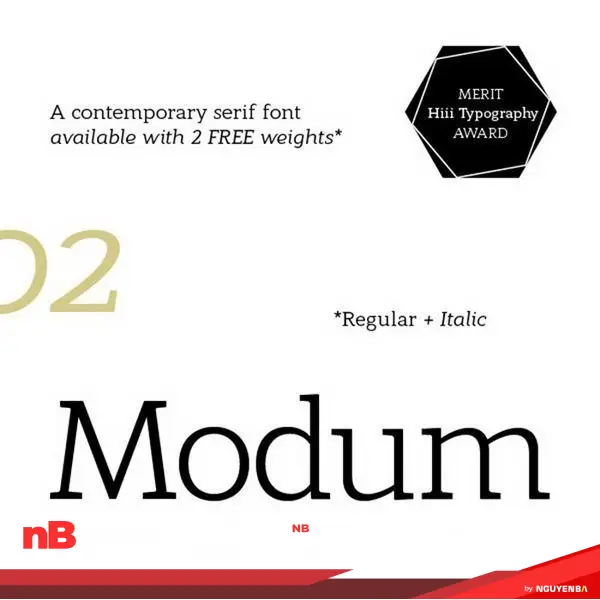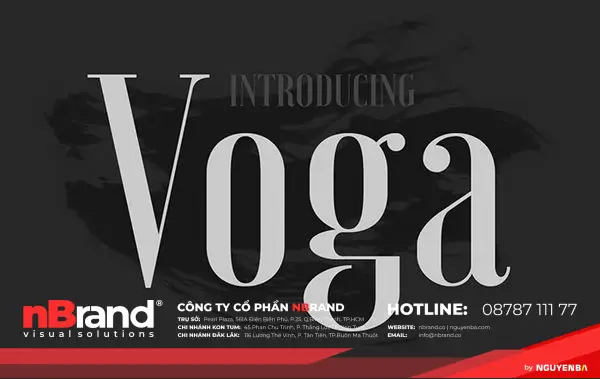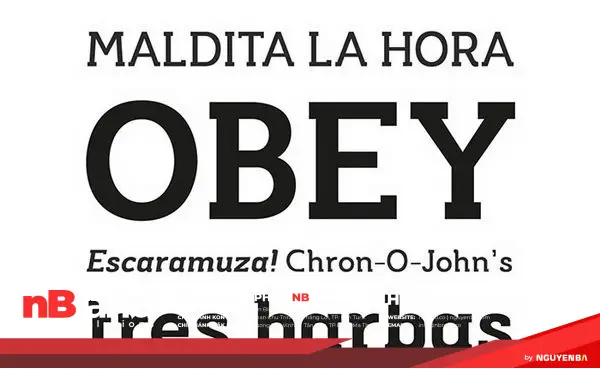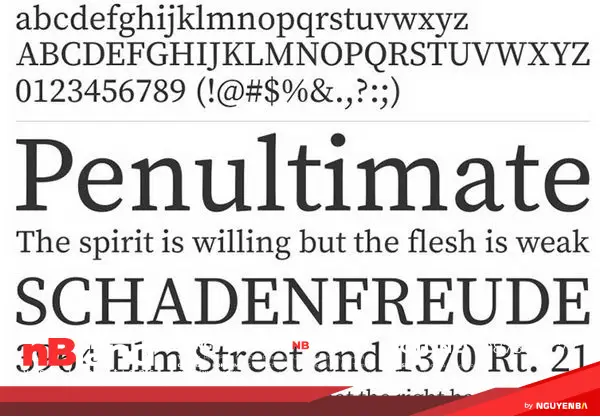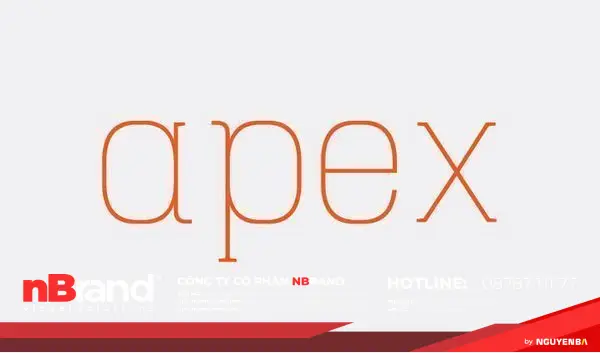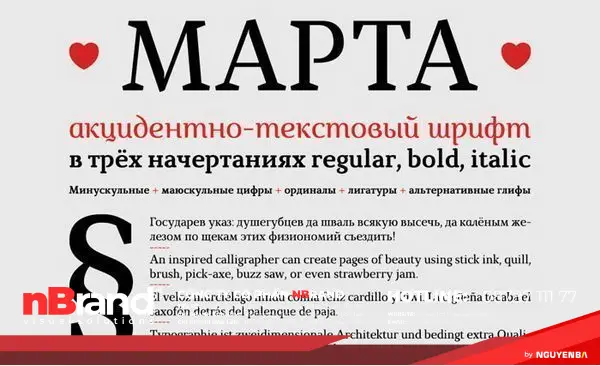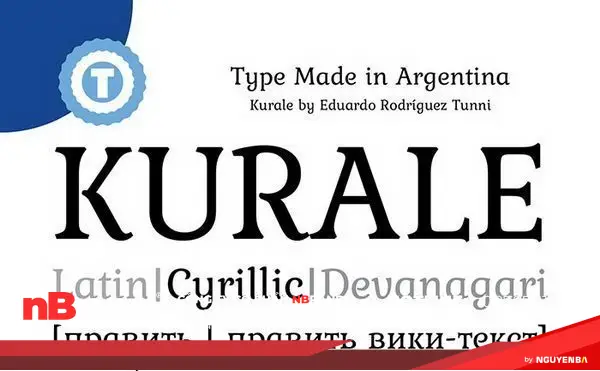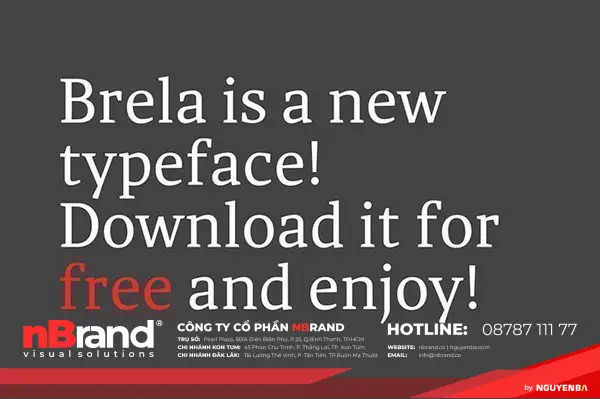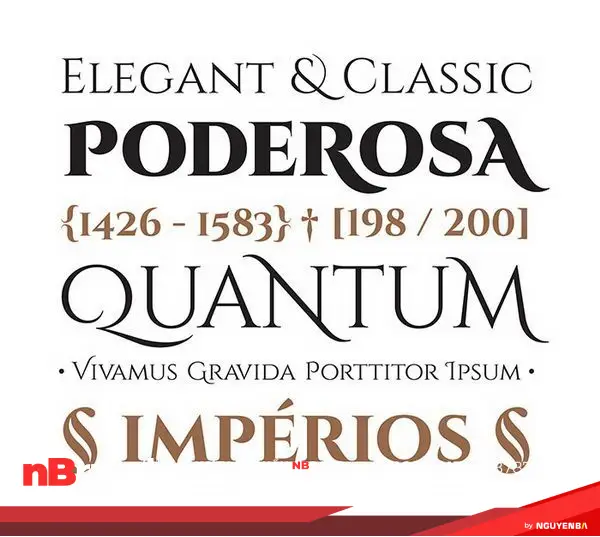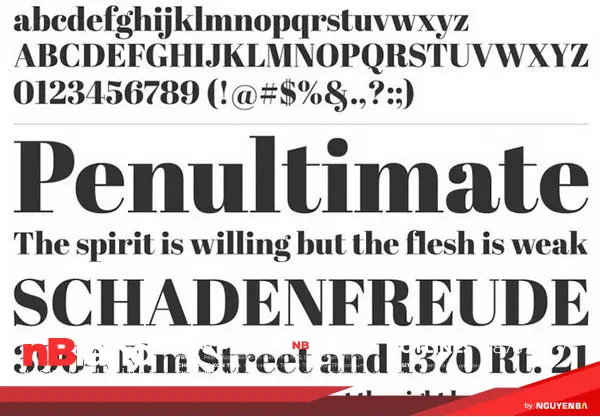
Chữ Serif rất phổ biến và thân thuộc; thường xuất hiện trong các tài liệu, sổ sách, đánh máy hàng ngày. Hầu hết mọi người sử dụng chữ serif hiện đại như Georgia, Garamond và Courier New như font chữ mặc định trên mạng; Time news Roman mặc định trên Word. Nếu bạn không có font serif trên máy tính xách tay hoặc máy tính bảng của bạn, bạn có thể dễ dàng tìm một font chữ theo kiểu serif trên mạng.
Những dạng chữ Serif đã thay đổi qua thời gian: Old Style (cuối 15 – đầu thế kỷ 18) phát triển thành Transitional – Chuyển tiếp (thế kỷ 18) và thêm Modern (cuối thể kỷ 18 – đầu thế kỷ 19). Bên cạnh đó Slab Serif xuất hiện đầu thế kỷ 19. Các nhà thiết kế thường tạo ra những mặt chữ mới của Serifs dựa trên lịch sử hình dạng của chúng.
Trong bài viết này, Designs xin giới thiệu với các độc giả các font serif hiện đại và phổ biến mà bạn có thể tải về miễn phí.
Aleo
Kiểu chữ Aleo được thiết kế theo phong cách Slab serif hiện đại bởi Alessio Laiso. Đặc điểm nổi bật của Aleo là các chi tiết bo tròn, cấu trúc thẳng tạo sự mạnh mẽ, cứng cáp và dễ đọc. Có 6 phong cách của Aleo được nhà thiết kế cung cấp bao gồm: đậm, vừa, sáng, nghiêng, đậm và thường.
Margot
Margot là một kiểu chữ được thiết kế và tối ưu hóa khi sử dụng nó trong các kích thước lớn. Ngoài ra Margot mang tới cảm giác vui vẻ, sôi động do đó hoàn toàn phù hợp khi in ấn ấn phẩm quảng cáo.
Calendas Plus
Modum
Kiểu chữ Modum có ảnh hưởng từ hình thức serif truyền thống và độ tương phản thấp. Các chi tiết tròn mịn được kết hợp khéo léo với các góc sắc nét tạo sự hài hòa. Do đó, Modum phù hợp với các dự án, văn bản phức tạp như bài xã luận, báo chí và sách dựa trên văn bản.
Atletico
Source Serif Pro
Serif Pro được thiết kế dựa theo xu hướng chuyển tiếp Sans với sự kết hợp giữa tỉ lệ vàng và màu sắc của typographic.
Hagin
Hagin là kiểu chữ miễn phí mới từ Fontfabric được xây dựng với dựa trên các đường nét hình học mạnh mẽ. Kiểu chữ có thể áp dụng cho bất kỳ loại thiết kế đồ họa – web, in ấn, đồ họa chuyển động và hoàn hảo cho áo thun và các mặt hàng khác như áp phích, logo.
Flagship
Kiểu chữ Flagship Slab Rounded được xây dựng và phát triển từ phong cách slab serif với đặc trưng bóng. Flagship cung cấp đầy đủ chữ thường và chữ hoa in nghiêng và in đậm.
Voga
Voga là một kiểu chữ Didone hiện đại với ba font: nghiêng, vừa và đậm. Voga mang lại cảm giác thanh lịch và với một số chữ độc đáo với sự kết hợp giữa đường congi với đường thẳng, cùng với đó là sự đổ bóng nhẹ đặc trưng.
Hapna
Hapna là một kiểu chữ serif các điệu đương đại với những đặc điểm hình học. Hapna bao gồm 241 ký tự chữ hoa và tính năng nguồn mở dành cho người sử dụng.
Lovato
Kiểu chữ Lovato được thiết kế theo phong cách thanh lịch, tinh tế với 2 màu sắc tương phản trắng đen. Với 5 font được cung cấp, Lovato phù hợp với những thiết kế rõ ràng, sắc nét, thời trang như với thiết kế thương hiệu, sách, poster.
Musket
Anglecia Pro Display
Anglecia Pro là sự kết hợp ba kiểu chữ serif phù hợp trong thiết kế biên tập. Trục đối xứng, hình thang đặc trưng và sự khác biệt khi chỉnh kích cỡ tiêu biểu cho ba kiểu chữ đặc trưng của serif.
Piron
Kiểu chữ Piron được thiết kế cẩn thận tới từng chi tiết, độ tương phản cao phù hợp với nhiều màn hình hiển thị. Do đố, Piron thường được sử dụng trong thiết kế web, in ấn đặc biệt là cho các tạp chí, tờ rơi, logo, áp phích, tờ rơi.
Gaspar
Kiểu chữ Gaspar được tạo ra bởi Carlos Alonso theo phong cách slab-serif. Gaspar có thể được sử dụng và hiển thị tốt trong trang web, tờ rơi, áp phích. Carlos cung cấp 2 font có sẵn là thường và nghiêng cho kiểu chữ này.
Bitter
Fenix
Fenix là một kiểu chữ serif thiết kế dựa trên thư pháp cho hiển thị kỹ thuật số và các văn bản. Tỷ lệ nó lại nhằm đạt được không gian chiều cao và chiều rộng. Fenix là thanh lịch với kích thước lớn và dễ đọc cùng một lúc, với rất nhiều nhịp điệu trong các kích cỡ nhỏ.
Brela
Brela là một kiểu chữ serif dành riêng cho thiết kế biên tập. Nhờ chiều cao và độ rộng lớn, Brela hoàn toàn dễ đọc với kích thước nhỏ. Ở kích thước lớn hơn các tính năng được nâng cao rất hoàn hảo cho các tiêu đề.
Marta
Marta bao gồm các chữ số, số La Mã, các chữ ghép, các ký hiệu, do đó có thể sử dụng kiểu chữ Marta có thể sử dụng trong thiết kế typography.
Akura Popo
Akura Popo là một font serif mang phong cách cổ điển đậm nét kết hợp cùng sự mạnh mẽ và cứng rắn. Akura phù hợp trong thiết kế logo, tiêu đề, thiết kế chủ đề thể thao.
Born
NOOA
Nooa là sự kết hợp tinh tế giữa các font serif và sans serif.
Chelsea
Tryst
Tryst được thiết kế mềm mại mang hơi hướng của thế kỉ 18 với độ sắc nét và tương phản cao.
Fritz
Kurale
Kiểu chữ Kurale bao gồm các chữ cái Latin, Cyrillic và Devanagari có nguồn gốc từ Gabriela. Kurale là một kiểu chữ serif với hình dạng mềm,với các nét cuỗi chữ được thiết ke như hình dạng tóc.
Cinzel
Cinzel được lấy cảm hứng trên bia của roman vào thế kỷ đầu tiên và được tạo dựng lại theo đúng tỷ lệ đó. Kiểu chữ này được thiết kế chủ yếu cho hiển thị trên Màn hình LED với độ tương phản lớn bảo đảm cho các font chữ sẽ hiện sắc nét.